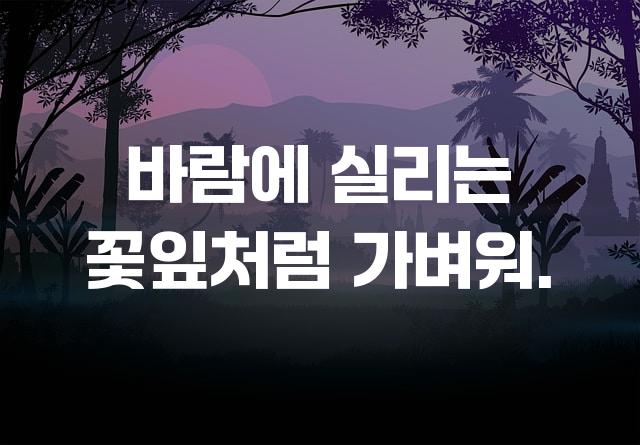
여기어때 잘난체는 제목용으로 완벽한 선택이며, 감각적인 꽉 찬 고딕 스타일에 둥근 고딕의 부드러움과 장식적 요소가 더해진 독특한 폰트입니다. 이 폰트는 간결함과 세련된 디자인을 동시에 제공하며, 모든 제목을 돋보이게 만듭니다.
기본 고딕, 둥근 스타일, 굵은 고딕, 장식 스타일, 감성적인, 단단함, 부드러움, 복실복실, 별모양/패턴, 길고/크고 계열의 생김새를 가지고 있으며
포스터, 소셜 미디어 등에서 자주 활용되며, 효과적인 메시지 전달에 적합합니다.
이 폰트는 이벤트/웨딩, 관광/여행 분야에 잘 어울리며,
친근한, 재미있는 느낌을 담고 있는 것이 특징입니다.